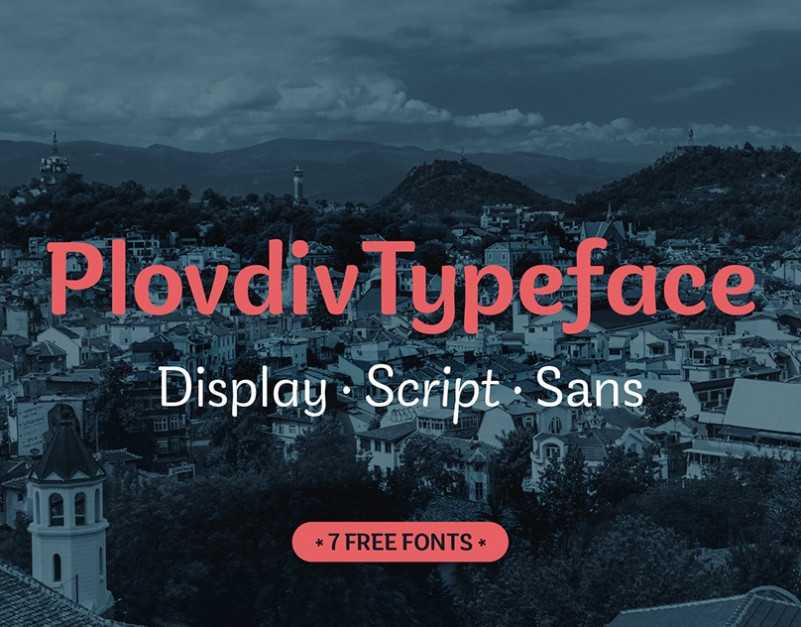
A fonte Plovdiv é uma família de 7 tipografias do tipo sans serif dedicada à bela cidade búlgara de Plovdiv. Inspirada na escrita a mão de cidadãos e amigos de Plovdiv, esta fonte está disponível gratuitamente para download como parte da iniciativa cultural Plovdiv – Capital Europeia da Cultura 2019. Esta parceria entre o Studio Punkt em Sofia e Typedepot, uma estúdio de tipografia na Búlgara, resultou num projeto que destaca a riqueza cultural desta cidade encantadora. Com sua influência única, as letras Plovdiv oferecem um toque autêntico e criativo para qualquer projeto visual. Suas linhas simples e leves refletem o charme do estilo de vida da cidade, combinando modernidade com arco-íris dos dias passados. Ideal tanto para aplicativos digitais quanto para criações impressas, a Plovdiv é uma fonte que se encaixa perfeitamente em projetos que buscam transmitir essa conexão única entre o belo e o contemporâneo de Plovdiv.